10 FONT CHỮ ĐẸP VÀ MỚI NHẤT TRONG THIẾT KẾ ĐỒ HỌA 2021
Để có một soạn thảo một văn bản thu hút và truyền tải thông điệp đến người đọc, chúng ta cần có cách trình bày đẹp mắt, dễ nhìn, dễ đọc vì thế chọn một font chữ thích hợp là rất cần thiết. Font chữ là các chữ cái, dấu câu, con số, ký tự, theo một loại, một định dạng. Ngoài ra bạn có thể thiết kế dựa trên font chữ để tạo nên các sản phẩm typography bắt mắt và có ứng dụng rất tốt trong việc quảng bá, truyền tải nội dung.
TOP 10 FONT CHỮ ĐẸP NHẤT TRONG THIẾT KẾ 2021
Một số trong số này là những phông chữ mới mà bạn có thể chưa nghe nói đến. Nhưng thiết kế đồ họa không bao giờ chỉ là về sự mới mẻ và thời thượng, vì vậy chúng tôi cũng đã bao gồm một số phông chữ cũ hơn.
1. Futura Now
Được tạo bởi Monotype và chứa 102 kiểu, Futura Now là phiên bản cuối cùng của Futura, sans-serif cổ điển định nghĩa kiểu chữ hiện đại. Thật thú vị, nó hiện cũng có sẵn dưới dạng một phông chữ có thể thay đổi.
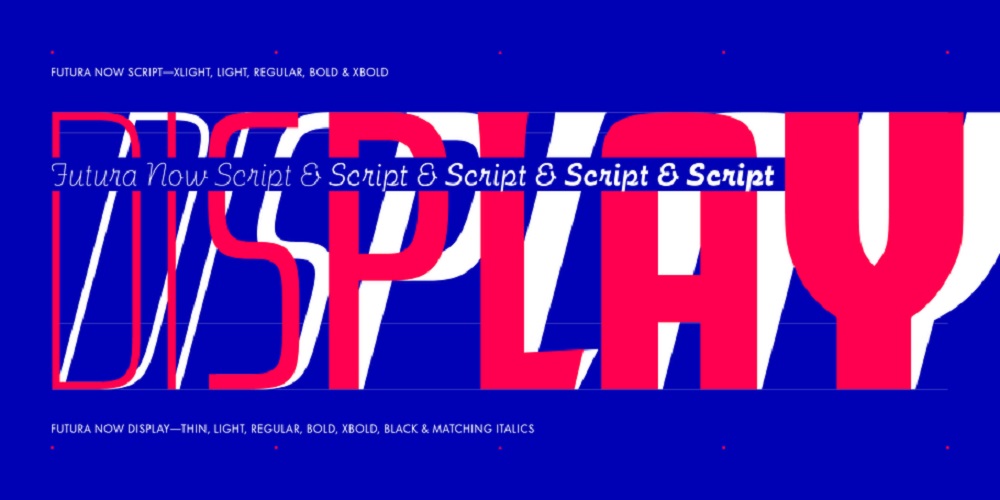
2. Juana
Juana đã được thiết kế bởi Eli Hernández vào năm 2020. Lấy cảm hứng từ kiểu chữ Jazmín, Juana được dự định là một thiết kế kiểu chữ phát triển hơn trong khi vẫn giữ được bản chất điển hình của phiên bản gốc. Sự tương phản mạnh mẽ giữa các nét dày và mỏng tạo ra một cái nhìn hài hòa và phong cách. Họ hoàn chỉnh có 8 trọng số cộng với chữ in nghiêng phù hợp và một phiên bản thay thế. Bộ ký tự mở rộng của Juana hỗ trợ hơn 200 ngôn ngữ dựa trên tiếng Latinh.
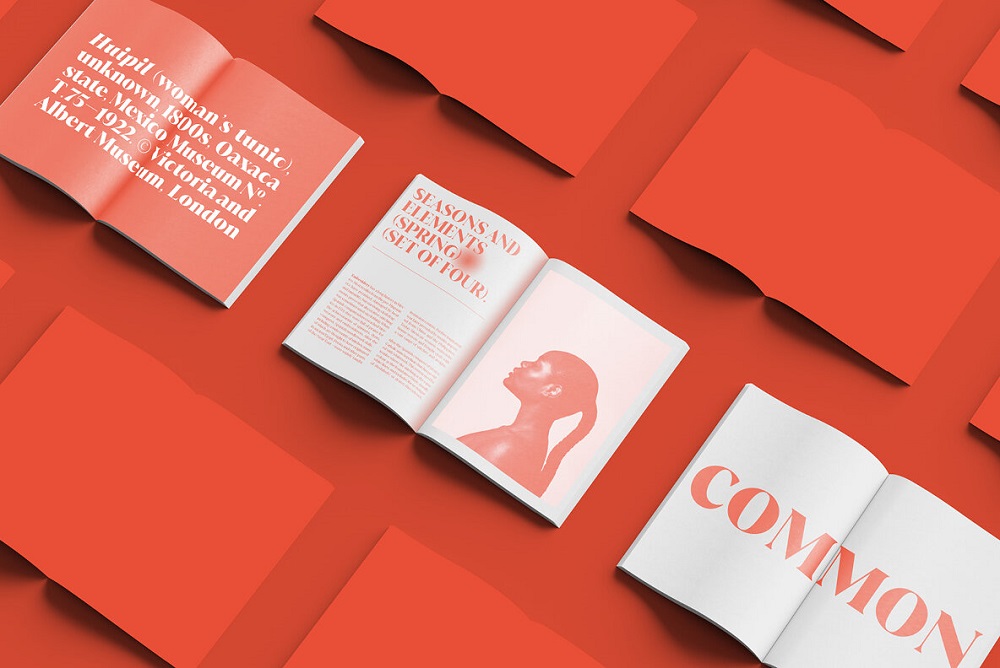
3. Brandon Grotesque
Brandon Grotesque từ nhà máy đúc kiểu Đức Phông chữ HVD, phông chữ được xuất bản vào năm 2010 nhưng không mất đi sự phổ biến trong những năm qua. Phông chữ OpenType được trang bị bộ ký tự mở rộng để hỗ trợ các ngôn ngữ Trung và Đông Âu cũng như Tây Âu.
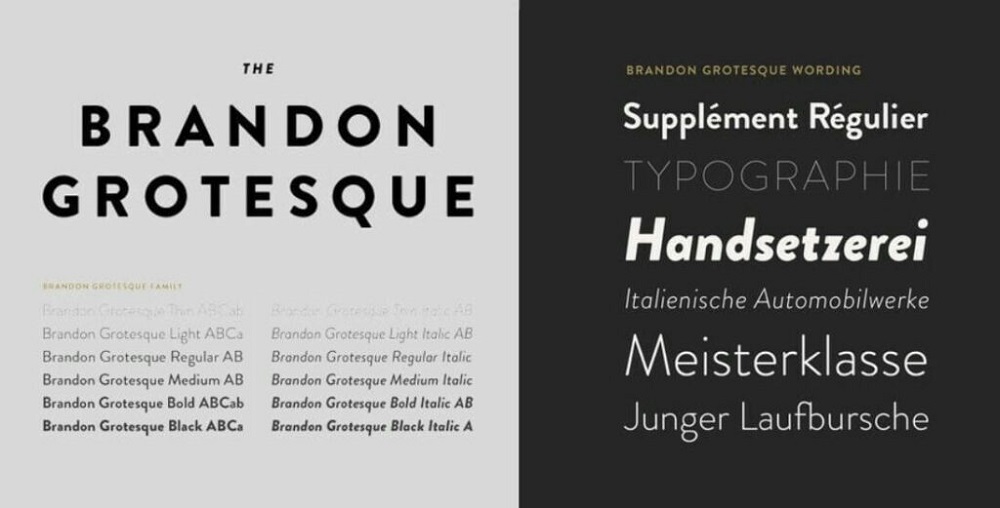
4. Valky
Được thiết kế và xuất bản bởi studio NEWFLIX.Bro, Valky là một kiểu chữ serif cổ điển khá độc đáo với các tính năng hiện đại. Bao gồm bốn kích thước, phông chữ hiển thị trang nhã bao gồm một số hình tượng và trang trí thay thế. Bộ ký tự của nó hỗ trợ nhiều ngôn ngữ. Valky rất thích hợp cho các dự án thiết kế đa dạng cũng như thiết kế logo, thương hiệu, bao bì, tiêu đề tạp chí, chỉ để nêu tên một số.
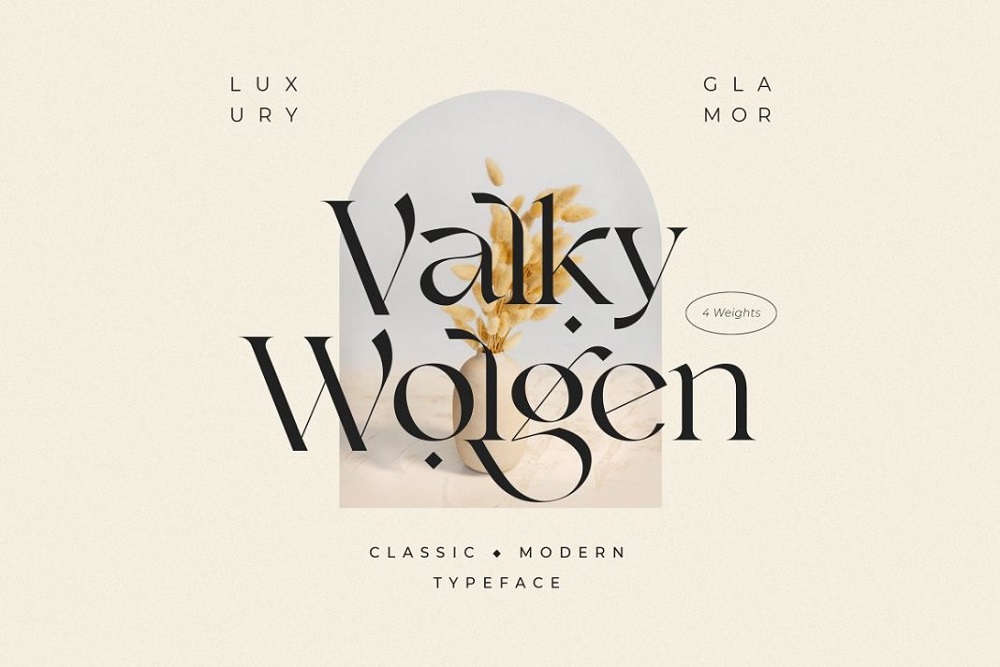
5. Glamour Absolute
Glamour Absolute là một serif đậm thanh lịch đi kèm với các đường cong cổ điển và hiện đại. Bằng cách này, kiểu chữ này có mọi thứ để kết hợp giữa phong cách cổ điển với hương vị hiện đại. Glamour Absolute có sẵn tại Creative Market và MyFonts.
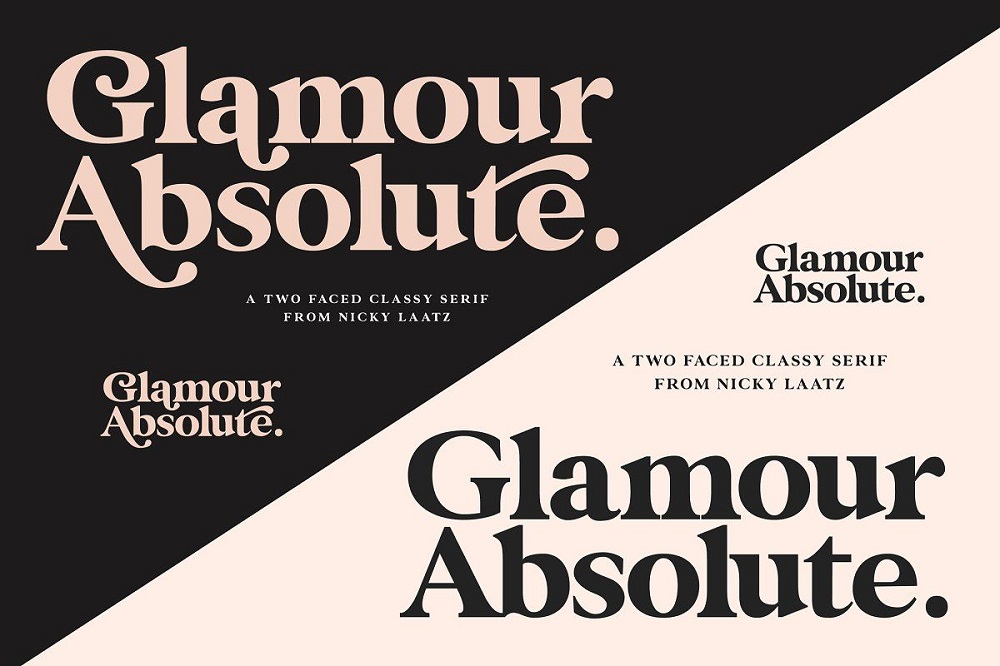
6. Acumin Pro
Được tạo ra bởi nhà thiết kế chính Robert Slimbach của Adobe, Acumin là một họ phông chữ sans-serif khổng lồ và linh hoạt có thể được sử dụng cho cả tiêu đề và các phần văn bản dài. Được trang bị với 90 kiểu dáng, nó đã được thiết kế đặc biệt để sử dụng trong thiết kế thông tin và mọi thứ yêu cầu một cái nhìn hiện đại và sạch sẽ.
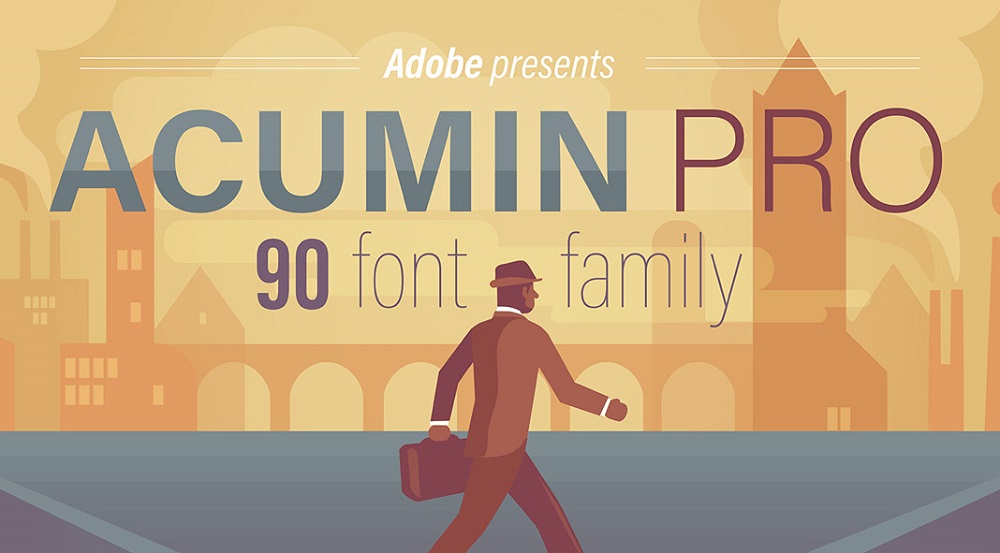
7. TT Norms Pro
Do thiết kế hiện đại cũng như các tính năng typographic đa dạng và nhiều khả năng sử dụng, TT Norms Pro đã trở thành một trong những phông chữ sans serif phổ biến nhất hiện nay. Font gồm 26 phông chữ được làm lại bao gồm kích thước khác nhau từ mỏng đến dày cộng với chữ in nghiêng phù hợp cũng như các đường viền bổ sung và các phiên bản thay đổi.
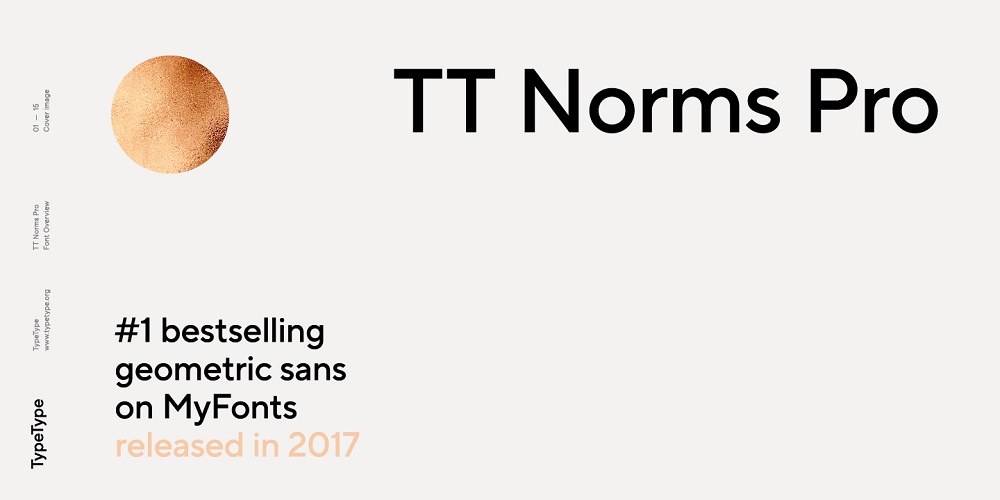
8. Bogart
Với tất cả nguồn cảm hứng từ các kiểu chữ mang tính biểu tượng khác nhau, Francesco Canovaro đã cố gắng tạo ra một phông chữ linh hoạt thể hiện tinh thần của kiểu chữ cổ điển. Tất cả chín trọng số cũng như các chữ nghiêng thực phù hợp có bộ ký tự mở rộng gồm hơn 1600 glyph, bao gồm 219 ngôn ngữ bao gồm các bảng chữ cái Latinh, Cyrillic và Hy Lạp.
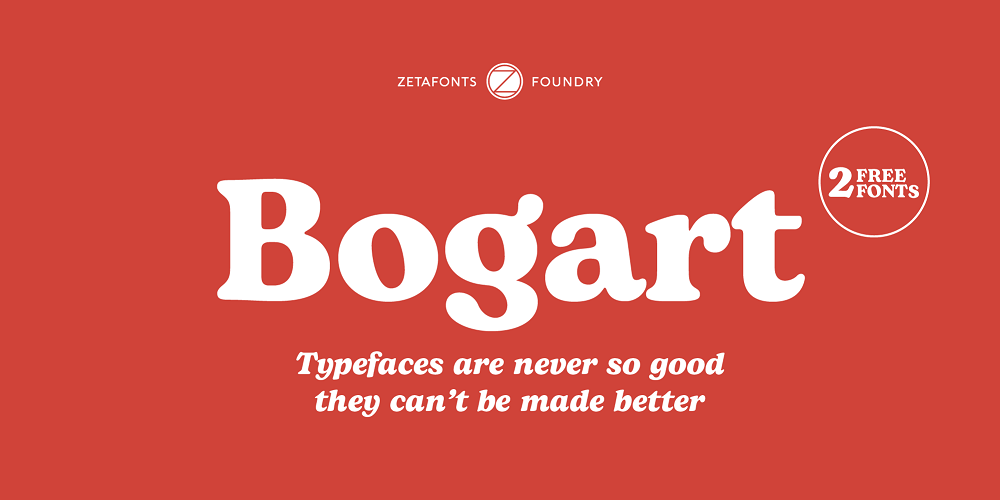
9. Circular
Circular là kiểu chữ sans-serif hình học được tạo ra bởi nhà thiết kế Thụy Sĩ Laurenz Brunner và được phát hành thông qua Lineto vào năm 2013, lấy cảm hứng từ font Futura của Paul Renner. Circular được xây dựng dựa trên các dạng thức của hình học, kết hợp giữa sự tối giản và ấm áp.
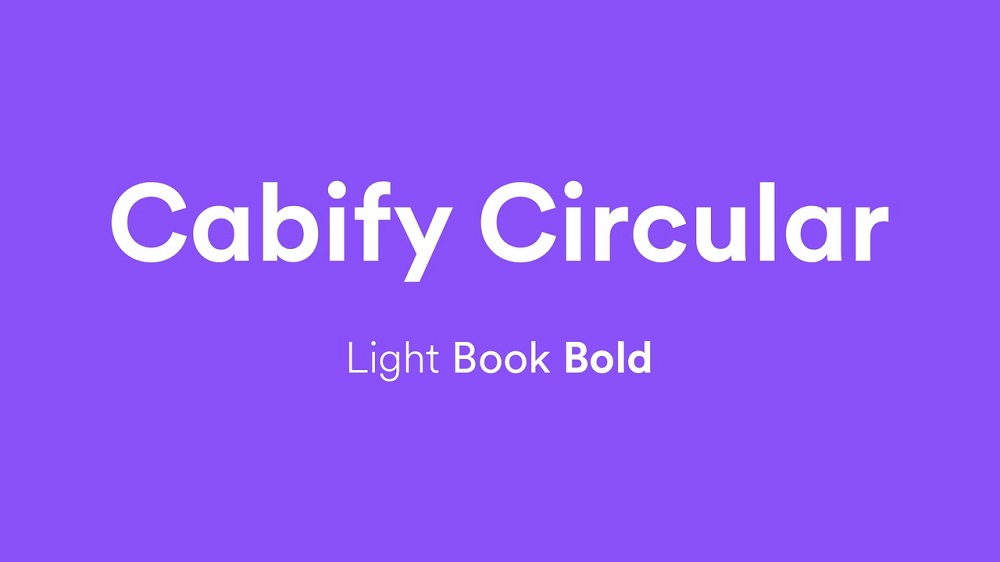
10. Bely
Bely là một phông chữ serif được thiết kế bởi Roxane Gataud , có các serifs hình tam giác, sắc nét và các khẩu độ mở. Font có sẵn trong hai kích thước với độ nghiêng phù hợp, cùng với phông chữ hiển thị, có mức độ tương phản rõ rệt giữa các nét dày và mỏng.